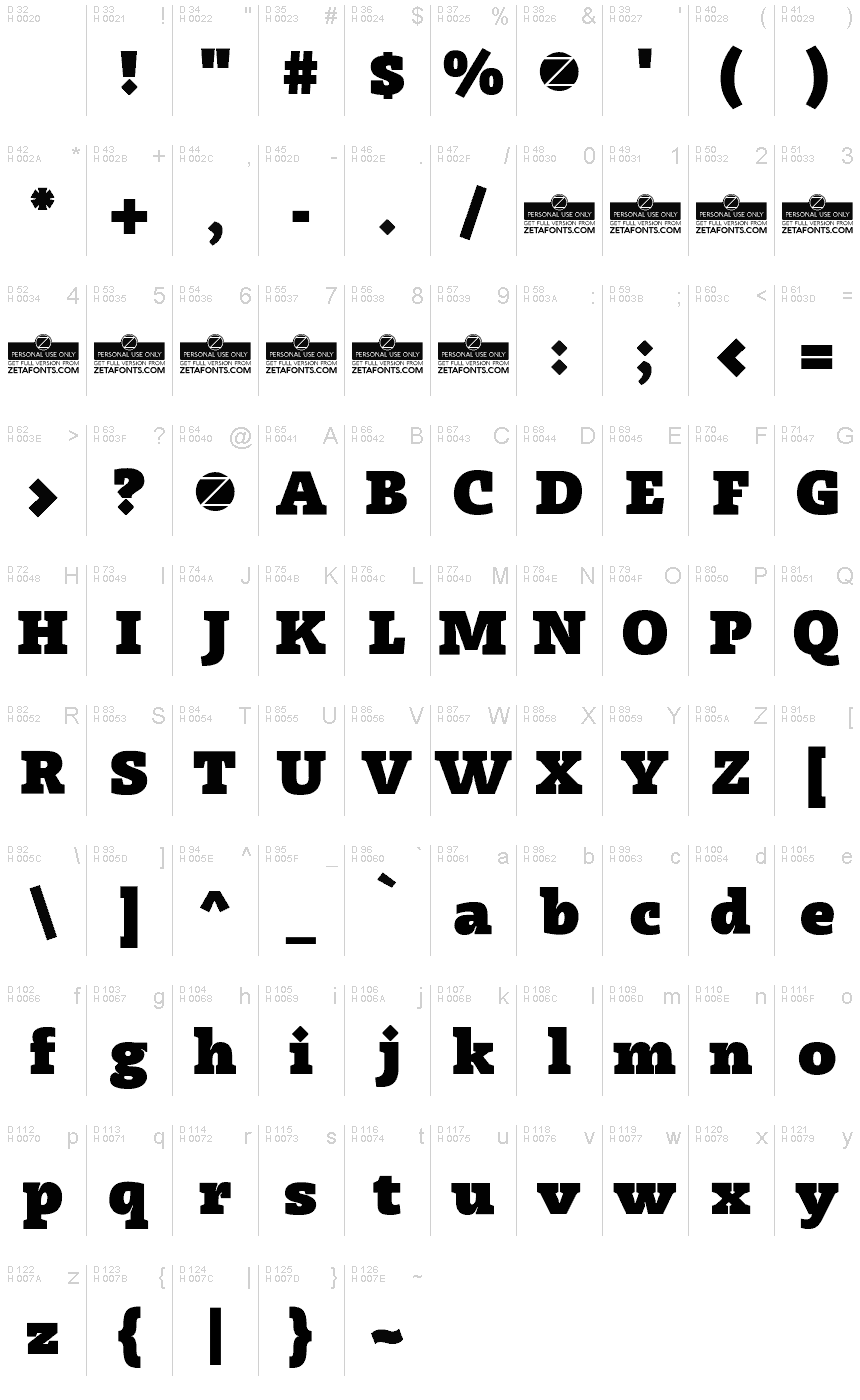
Radcliffe je rodina písem navržená v roce 2018 Cosimem Lorenzem Pancinim a Andreou Tartarellim jako reinterpretace tradičního clarendonového designu, která hledá podobu „současné klasiky“. Radcliffe je stvořen pro eleganci a vyznačuje se silnými serify s nábehem, vertikální osou a nízkým kontrastem, typickým pro Clarendony, vytříbeným humanistickým nádechem a kaligrafickým přístupem, který je patrný v kurzívách.
Primárně určená jako display písmo se širokou škálou jemně vyladěných řezů pro redakční účely a tvorbu log, byla rodina Radcliffe doplněna o Radcliffe Text. Ta byla vyvinuta v pěti řezech s větší střední výškou písma (x-height) a mírně zúženými proporcemi, což umožňuje maximální čitelnost v dlouhých textech na webu a při malé velikosti.
Rodina také zahrnuje dva výrazné řezy Radcliffe Casual, navržené s estetikou obráceného kontrastu, která se skvěle hodí pro vaše klubové aktivity. Všechna písma Radcliffe obsahují plné funkce OpenType se stylistickými alternativami, volitelnými ligaturami, pozičními formami číslic, swash tvary (v kurzívách) a plnou jazykovou podporou pro více než 70 jazyků používajících latinku a cyrilici.
Radcliffe Display